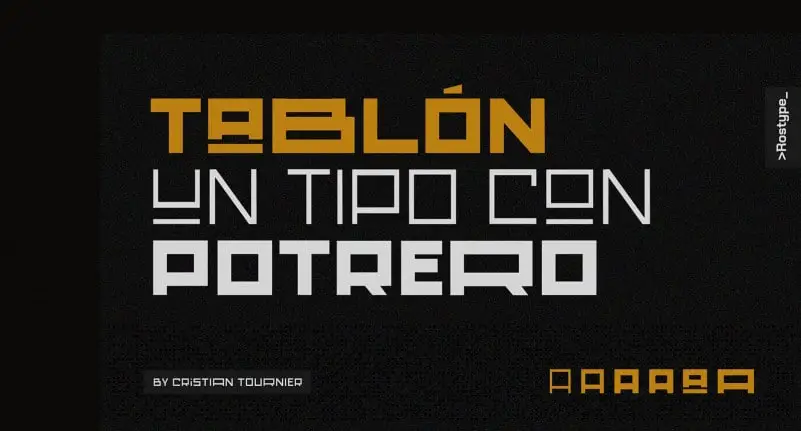
Tablón Display Font é uma tipografia moderna e dinâmica projetada para seus próximos projetos visuais. Inspirada na tipografia antiga usada nos sinais do Matienzo Club, um clube de Rosario, Argentina, a fonte se destaca pelo seu tom atemporal misturado com elementos atuais, como colorido e contraste. Seu design é uma fusão perfeita de energia esportiva e harmonia gráfica. Além disso, a família da font inclui três pesos variáveis: Regular, Medium e Black, e um tipo redondo, além de caracteres diacríticos, pontuação e sinais alternativos em todas as suas variações, aspectos essenciais da tipografia moderna que tornam a fonte funcional e interessante. Tablón Display é uma escolha ideal para criar projetos visuais atemporais e contemporâneos ao mesmo tempo.